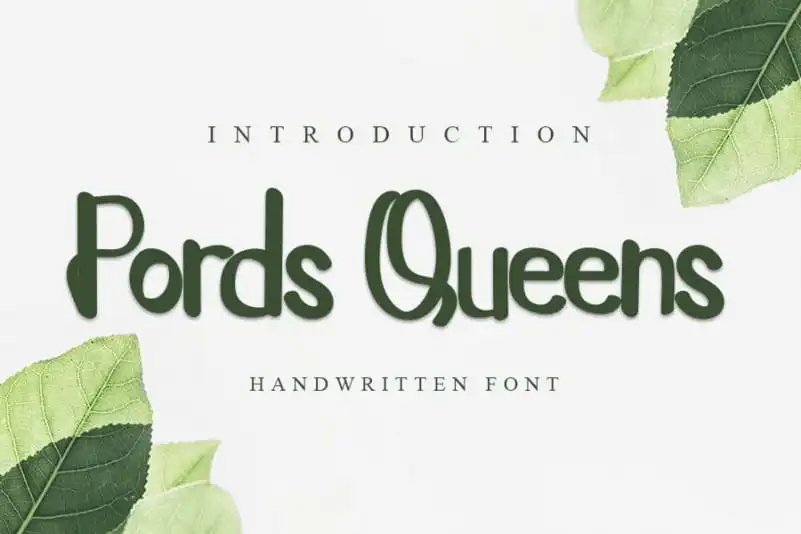
Pords Queens Script Font – Download Grátis
A Pords Queens Script Font é uma seleção única entre as fuentes serifas. Ela captura a elegância da escrita por mão livre enquanto também possui uma sensação contemporânea e atualizada, garantindo que sua utilização atenda a um amplo espectro de ideias criativas. Seja para lembretes, títulos ou materiais de estação, esta fonte se destaca pelas suas capacidades multifuncionais, tornando-a uma escolha ideal para designers em busca de uma aparição única e moderna no seu próximo projeto. Engajante por natureza, a Pords Queens Script Font é uma ótima adição para qualquer designer que procura um recurso visual único para ilustrar seus trabalhos de forma impecável.